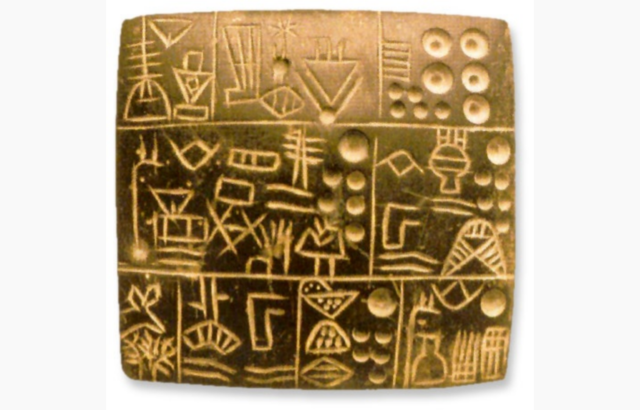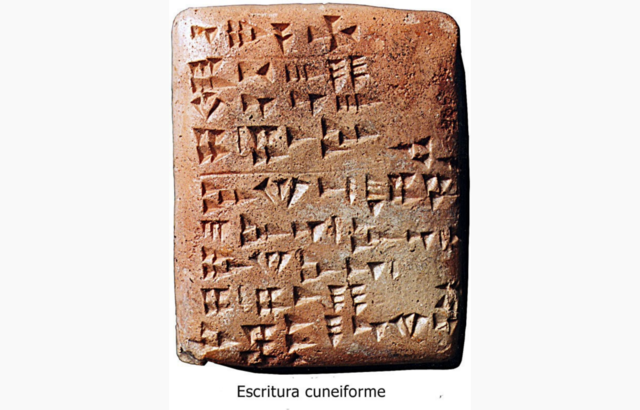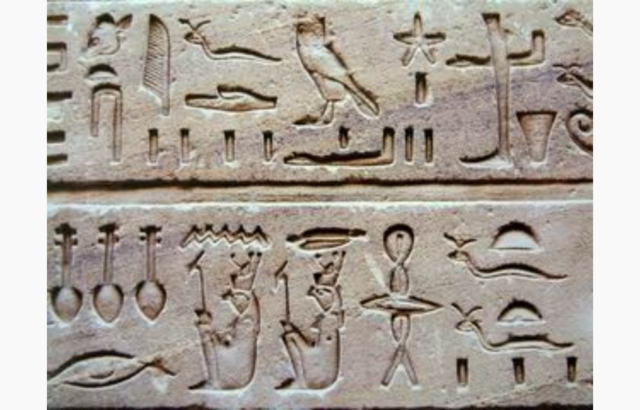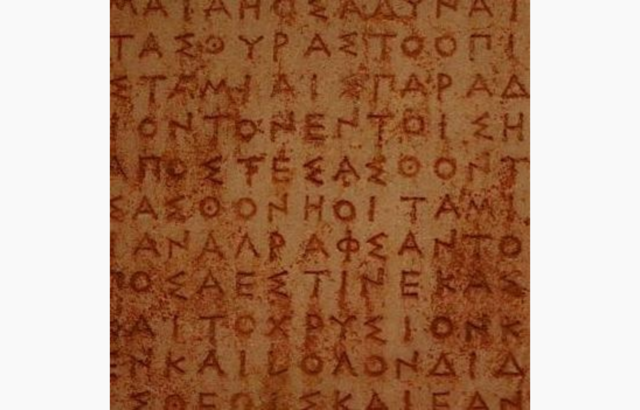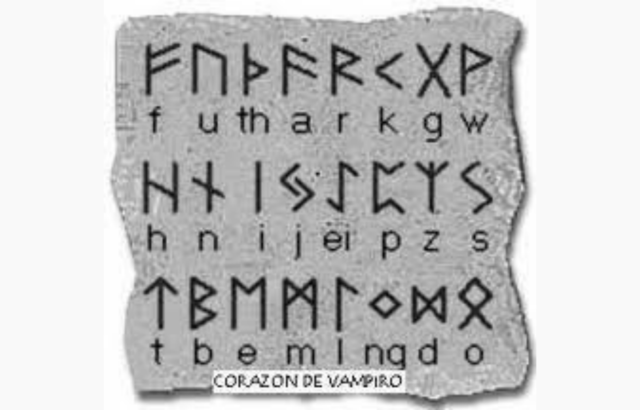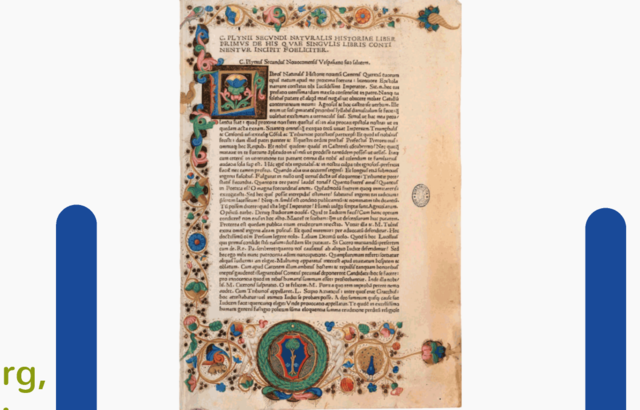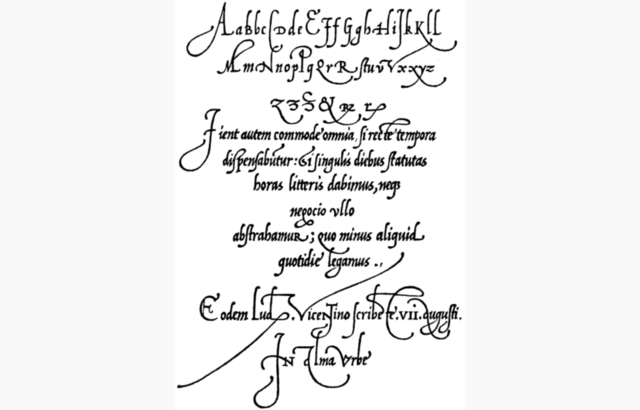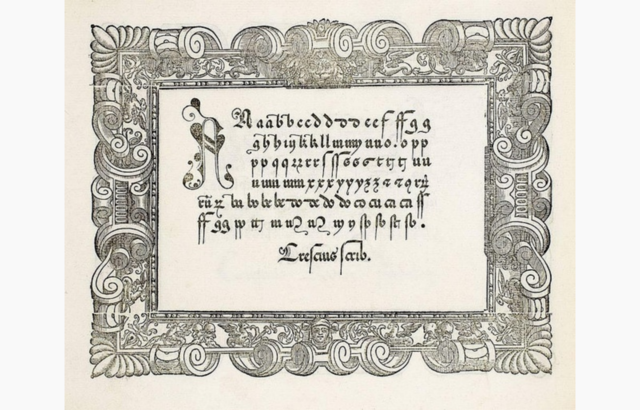
La pintura rupestre es una de las manifestaciones artísticas más antiguas que hayan subsistido hasta nuestros días y también la primer forma en representar lo que pasaba en el día a día de los cavernícolas -
La Prehistoria es la época que va desde la aparición de los primeros seres humanos hasta la invención de la escritura. División de la Prehistoria: 2.500.000 años a.C. hasta 3.500 años a.C.
Las pictografías (del latín pictum: relativo a pintar, y del griego grapho: trazar)son grafismos realizados sobre las rocas mediante la aplicación de pigmentos. Es comúnmente aceptada como una de las formas más antiguas de expresión escrita. -
Es comúnmente aceptada como una de las formas más antiguas de expresión escrita y se escribió originalmente sobre tablillas de arcilla húmeda, mediante un tallo vegetal biselado en forma de cuña, de ahí su nombre. Fue desarrollada en Mesopotamia. -
La Edad Antigua o Antigüedad es un periodo tradicional, muy utilizado en la periodización de la historia humana, definido por el surgimiento y desarrollo de las primeras civilizaciones que tuvieron escritura, llamadas por ello antiguas.
Fueron un sistema de escritura inventado por los antiguos egipcios quienes usaron tres tipos básicos de escritura: jeroglífica, hierática y demótica; esta última corresponde al Periodo tardío de Egipto. -
Los chinos desarrollan la caligrafía y usan logos-gramas -
Los fenicios desarrollan el proto alfabeto ( 20 signos mágicos, consonantes), fue el primer alfabeto fonético. -
El sistema de escritura griego es alfabético y tiene su origen en siglo XI a. C. las primeras inscripciones son del siglo VIII a. C. y el sentido de la escritura es de derecha a izquierda o en bustrófedon (designa al tipo de escritura o al modo de escribir que consiste en redactar alternativamente un renglón de izquierda a derecha y el siguiente de derecha a izquierda o viceversa.) -
Los romanos no inventaron este alfabeto, sino que lo adoptaron de los Etruscos, quienes a su vez tomaron las letras del alfabeto griego. Los etruscos contaban con 26 letras en su alfabeto, mientras que los romanos, cuando lo acogieron primeramente, conformaron el suyo con sólo 21. -
Inicios La Edad Media o Medievo es el período histórico de la civilización occidental comprendido entre el siglo V y el XV. Su inicio se sitúa en el año 476, el año de la caída del Imperio romano de Occidente, y su final en 1492, año en el que Colón llegó a América.
Johann Gensfleisch Zum Gutenberg, desarrollo en Alemania una técnica para elaborar moldes de tipos que se utilizarían para la impresión de letras individuales. Conrad Sweynheym y Arnold Pannartz, establecieron la primera imprenta de Italia, en el Monasterio Benedicto de Subiaco. -
Conrad Sweynheym y Arnold Pannartz, establecieron la primera imprenta de Italia, en el Monasterio Benedicto de Subiaco. -
Nicolás Jenson, uno de los tipográficos más importantes de la historia por componer "De Praeparatione Evangelica" de Eusebio en 1470, obra que representa el crecimiento del diseño de tipos romanos. -
Guillaume Le Roy introdujo la imprenta en Lyon, Francia en 1473; cinco años después se imprime el libro "Le Mirover de la Rédemption", utilizando grabados en madera importados de Basilea. -
Evolución De La Tipografía.
Ludovico Vicentino degli Arrighi creó el primer manual de escritura del Siglo XVI. En 1523 publico un segundo manual realizado con bloques de madera, impresas con tipos itálicos que él diseñó. -
Geoffroy Tory fue un reformador de la lengua francesa y su trabajo mas importante fue Champfleury publicado en 1529, el que medita sobre la escritura, proporción y el significado de las letras. -
1530 y 1585 las novedades tipográficas tienen su origen en Francia en lo que se denomina Edad de Oro de la tipografía francesa y aparte de ediciones a mano, muestra una creación de tipos verdaderamente interesante -
Blado produce y publica "II Perfetto Scrittore" de Giovanni Francesco Cresci, uno de los libros clásicos sobre letras. -
El Rey Felipe II de España comiso a Christophe Plantin para que trabajara en la "Biblia Regia", la cual fue impresa en 5 lenguas: hebreo, griego, arameo, latin y siriaco. -
Se imprimen los libros de bolsillo clásicos;
Don Quijote de la Mancha, de Miguel de Cervantes.
los tipos que se utilizaron fueron grabados por Christoffel van Dijck de Ámsterdam. -
Luis XIV ordeno la creación de un comité de eruditos para la creación de un nuevo tipo que fuera diseñado bajo principios científicos. Cada letra estaba construida sobre una cuadricula que contenia 2304 cuadros, Philippe Grandjean grabo los punzones -
Pierre Simon Fournier el joven, inicio la estandarizacion del tamaño de los tipos al pubicar su "Primera Tabla de Proporciones" en 1737. -
Se grabo un tipo etrusco San serif basado en formas de 2000 años de antigüedad, probablemente fue el primer tipo de sans serif que se haya hecho, no eran novedosos, su popularidad se debía a la buena legibilidad y textura. -